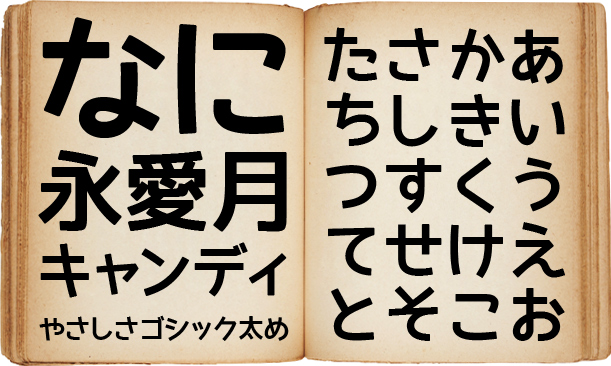
やさしさアンチックフォントのアップデート〜TrueType同梱
やさしさアンチックフォントのアップデートを行いました。
大きな修正というか文字自体の変更は無いのですが
漫画用のフォントが好評であれば
また作りたいと思います。
とはいえ次に公開するのは明朝体か
タイポスやフォーク(モリサワ)的なのになる可能性が高いです。
やさしさゴシックボールドの正式公開
一部の文字でパスがおかしくなっていたので
「やさしさゴシックボールド」を修正し先日Ver1.1としました。
これで正式公開ということにします。
もちろん1.0でも使えますがいくつかの文字でパスが崩れています。